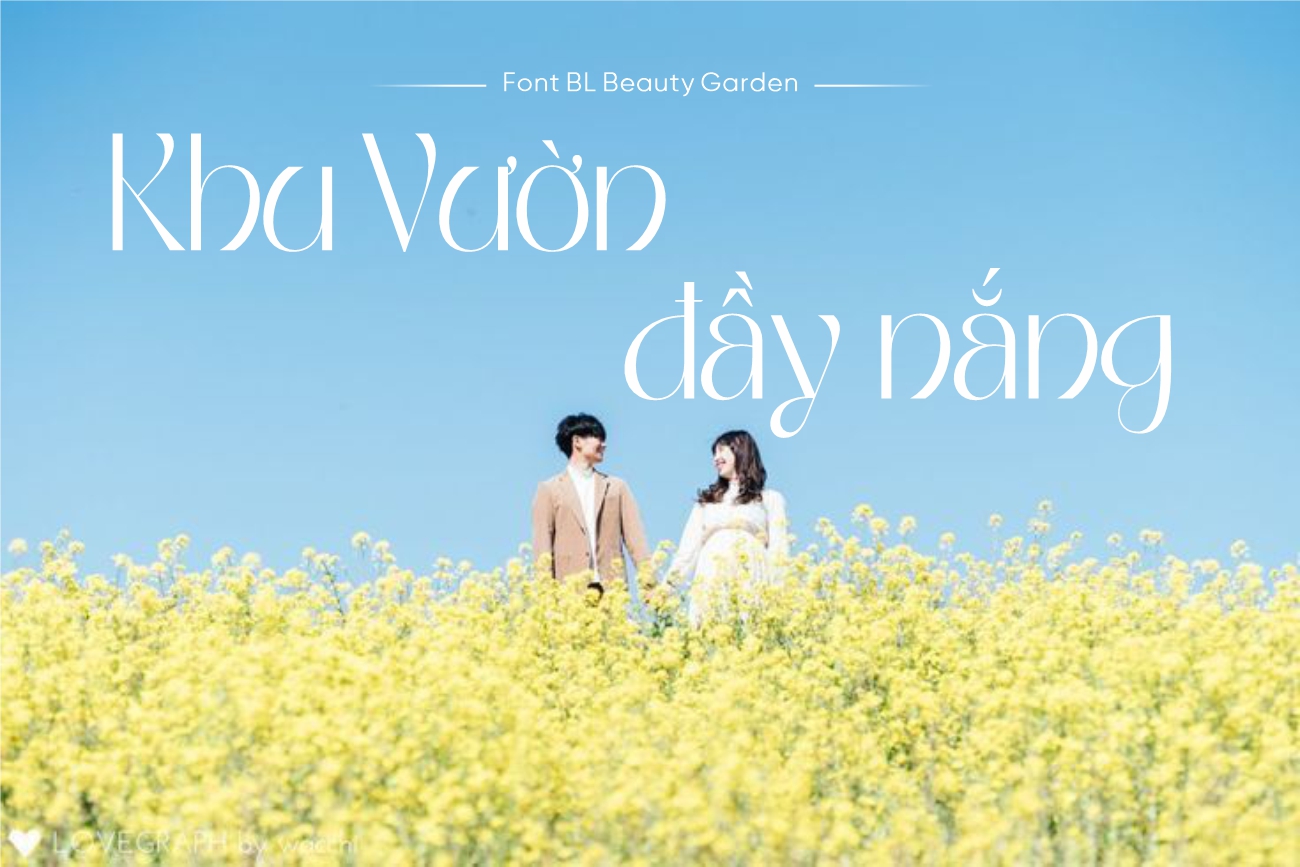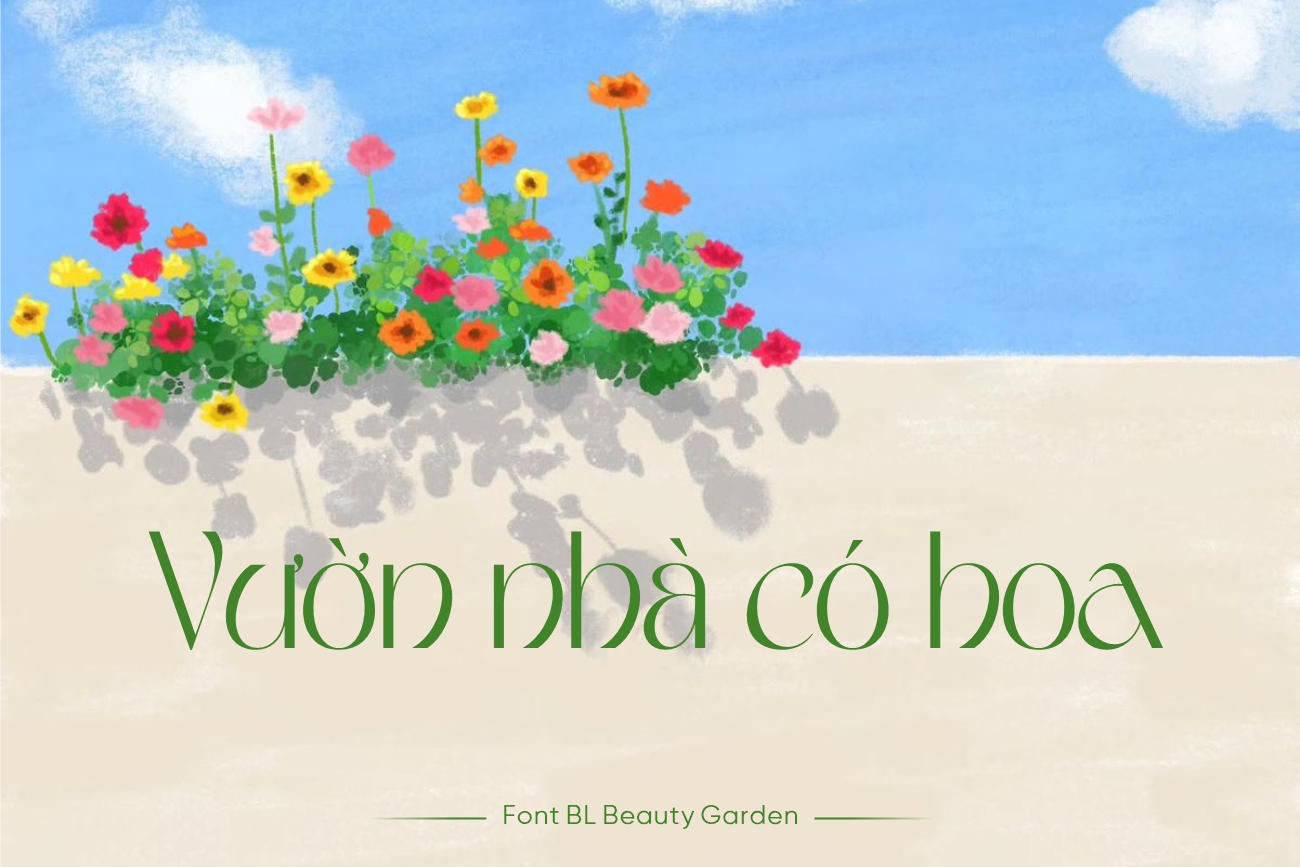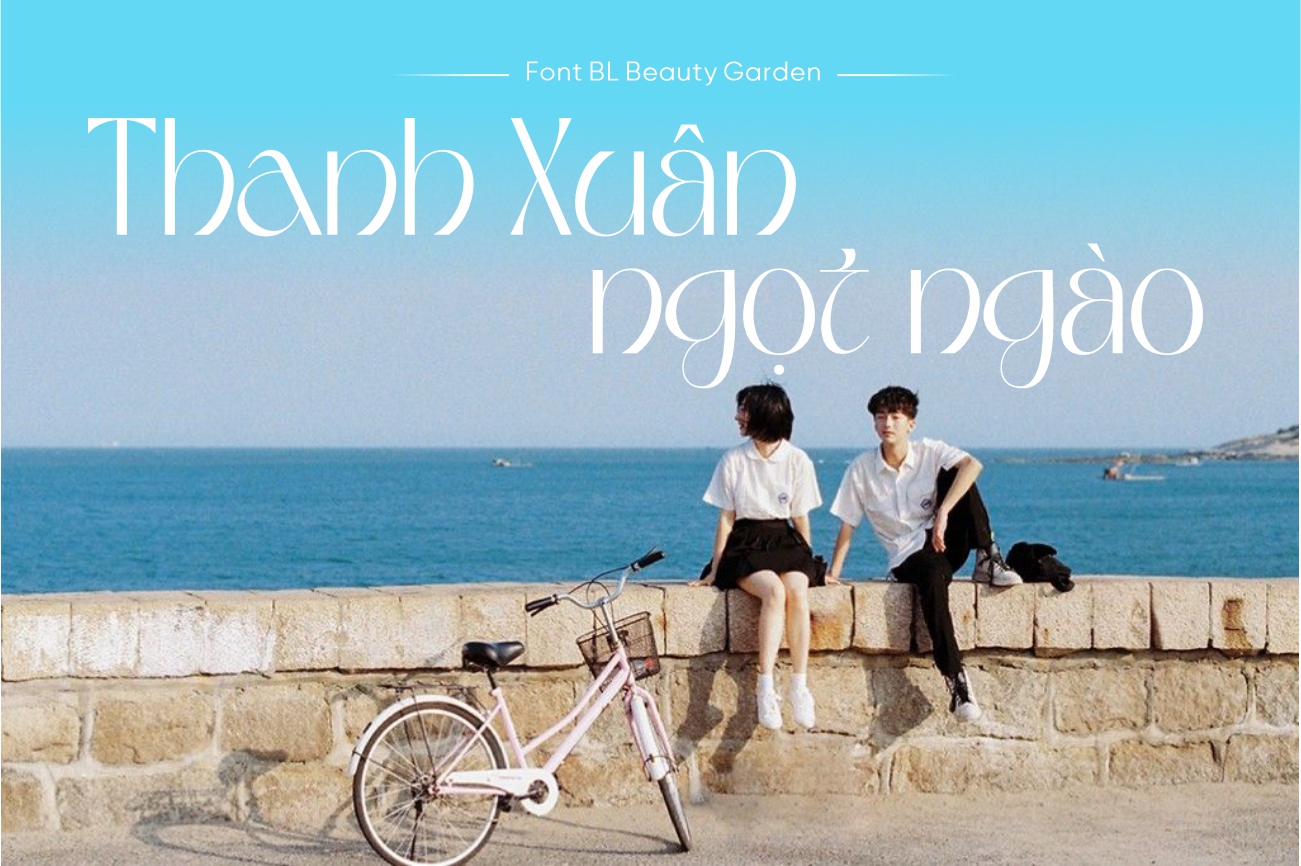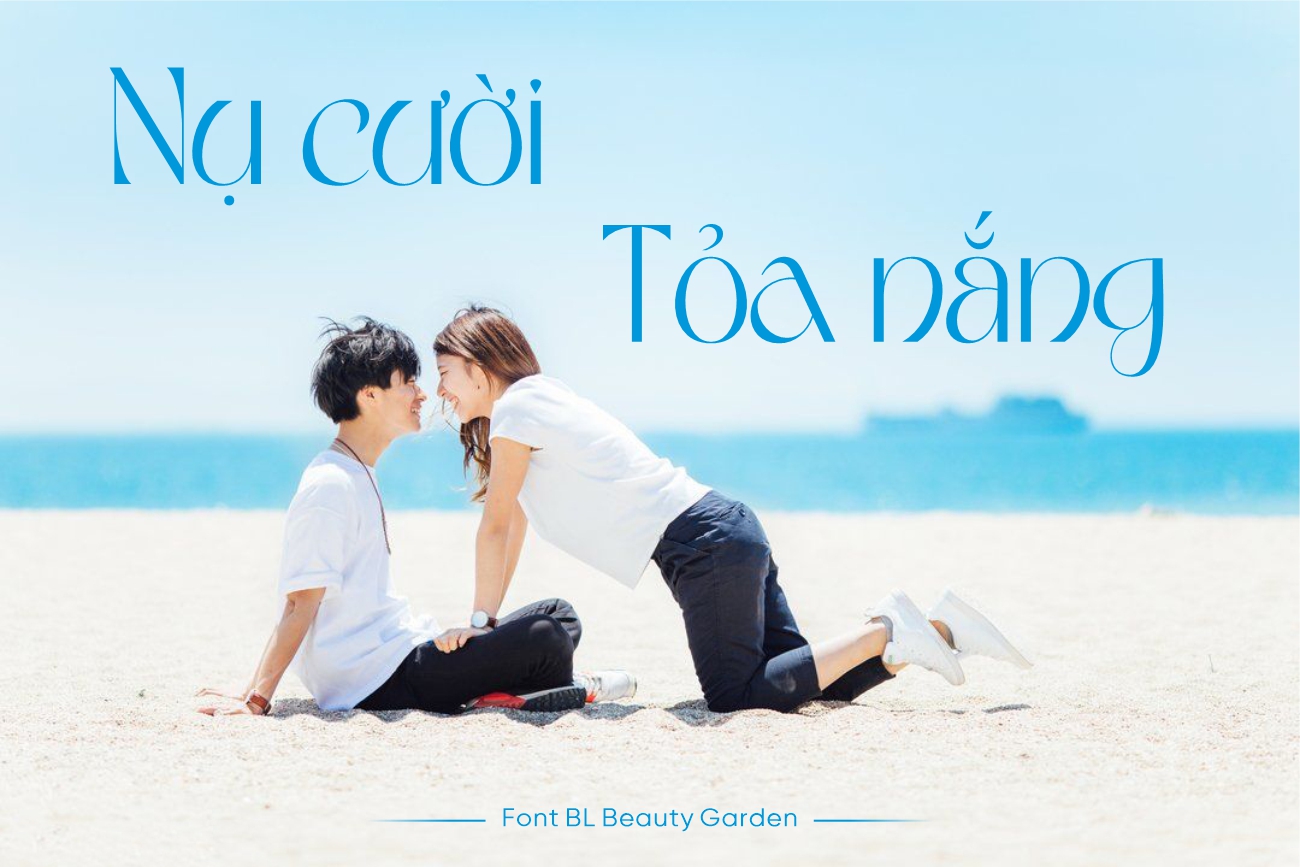
BL Beauty Garden
BL Beauty Garden thường được xem là lựa chọn hoàn hảo cho những ai muốn mang đến sự dịu dàng, ngọt ngào và cuốn hút trong thiết kế.
🔹 Đặc điểm nổi bật:
Kiểu chữ không chân (sans serif), nét chữ gọn gàng và cân đối.
Phong cách tinh tế, hiện đại nhưng vẫn giữ sự mềm mại nhẹ nhàng.
Dễ dàng kết hợp với Beauty Garden Script: script cho tiêu đề bay bổng – sans serif cho tagline, nội dung phụ.
Thích hợp với nhiều phong cách: wedding, thời trang, mỹ phẩm, lifestyle, branding.
💡 Ứng dụng thực tế:
Logo thương hiệu: kết hợp script để tạo điểm nhấn, sans serif làm nền tảng chắc chắn.
Thiệp cưới & thiệp mời: chữ chính dùng sans serif để dễ đọc, tiêu đề hoặc tên riêng dùng script nổi bật.
Ấn phẩm quảng bá & social media: vừa sang trọng vừa rõ ràng trên nhiều nền tảng.